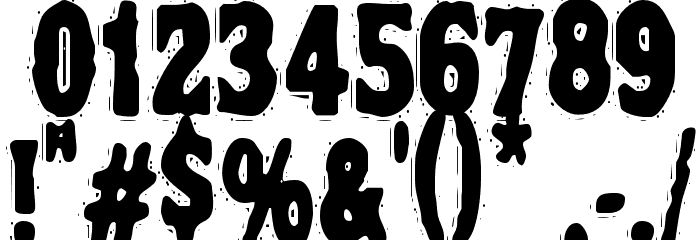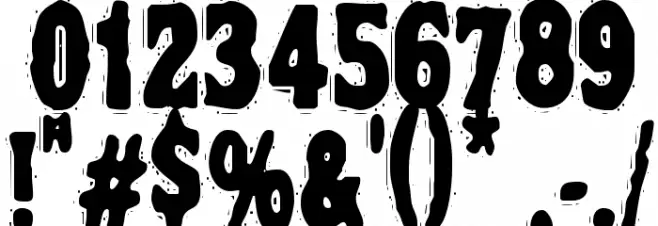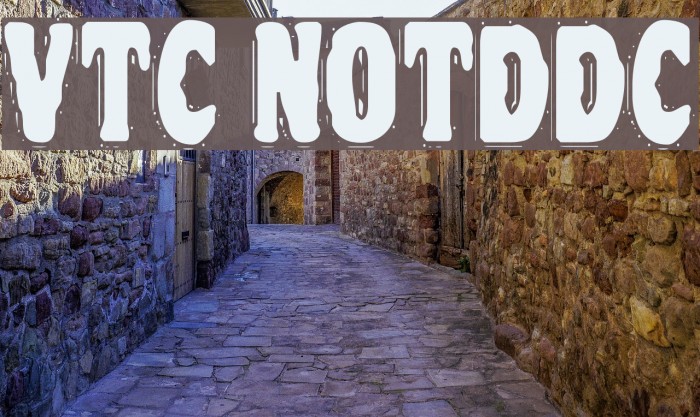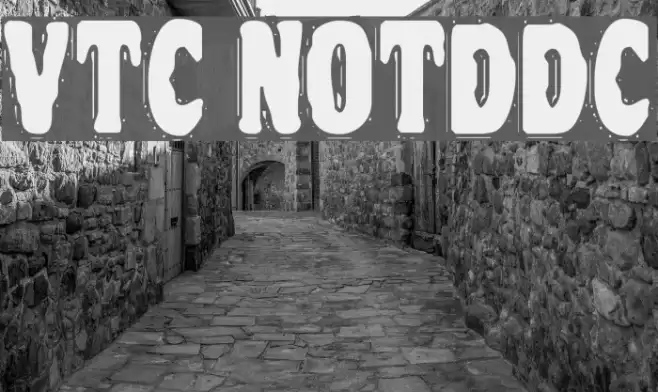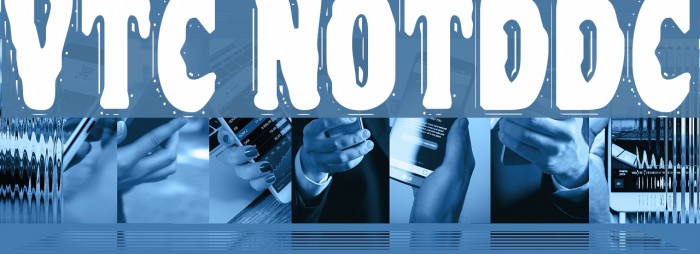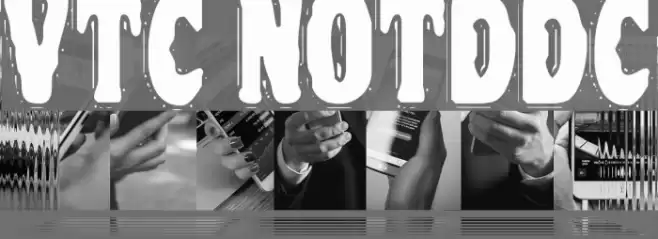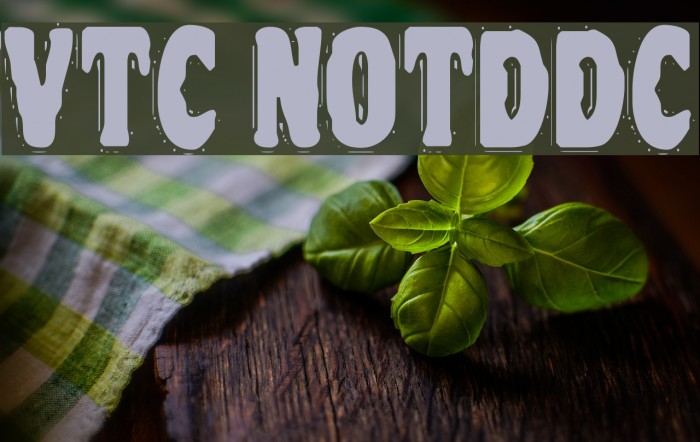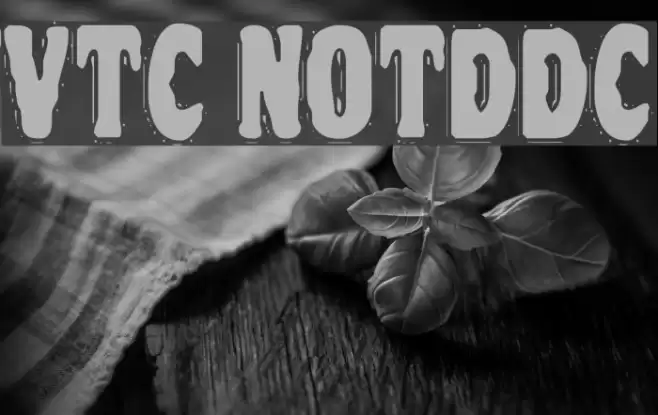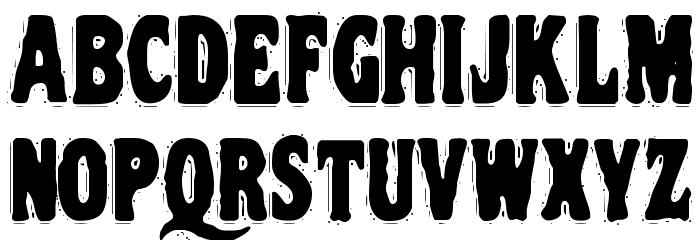
VTC NightOfTheDrippyDeadCaps Font
| Cas d'utilisation | Headlines, Posters, Logos |
| Projets proposés | Ideal for Halloween-themed designs, horror movie posters, party invitations, and any project requiring a spooky or playful aesthetic. |